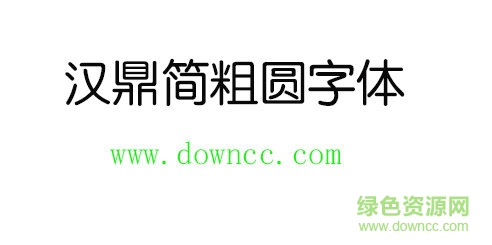
漢鼎簡(jiǎn)粗圓是一款藝術(shù)字體,看起來(lái)渾厚一體、落落大方,適用于做藝術(shù)標(biāo)題、重點(diǎn)介紹等,是生活中在廣告設(shè)計(jì)上比較常見(jiàn)的一款字體類型,而且在本站下載的該字體是可以永久免費(fèi)使用的,你可別錯(cuò)過(guò)了,有需要的朋友可以來(lái)綠色資源網(wǎng)下載哦!